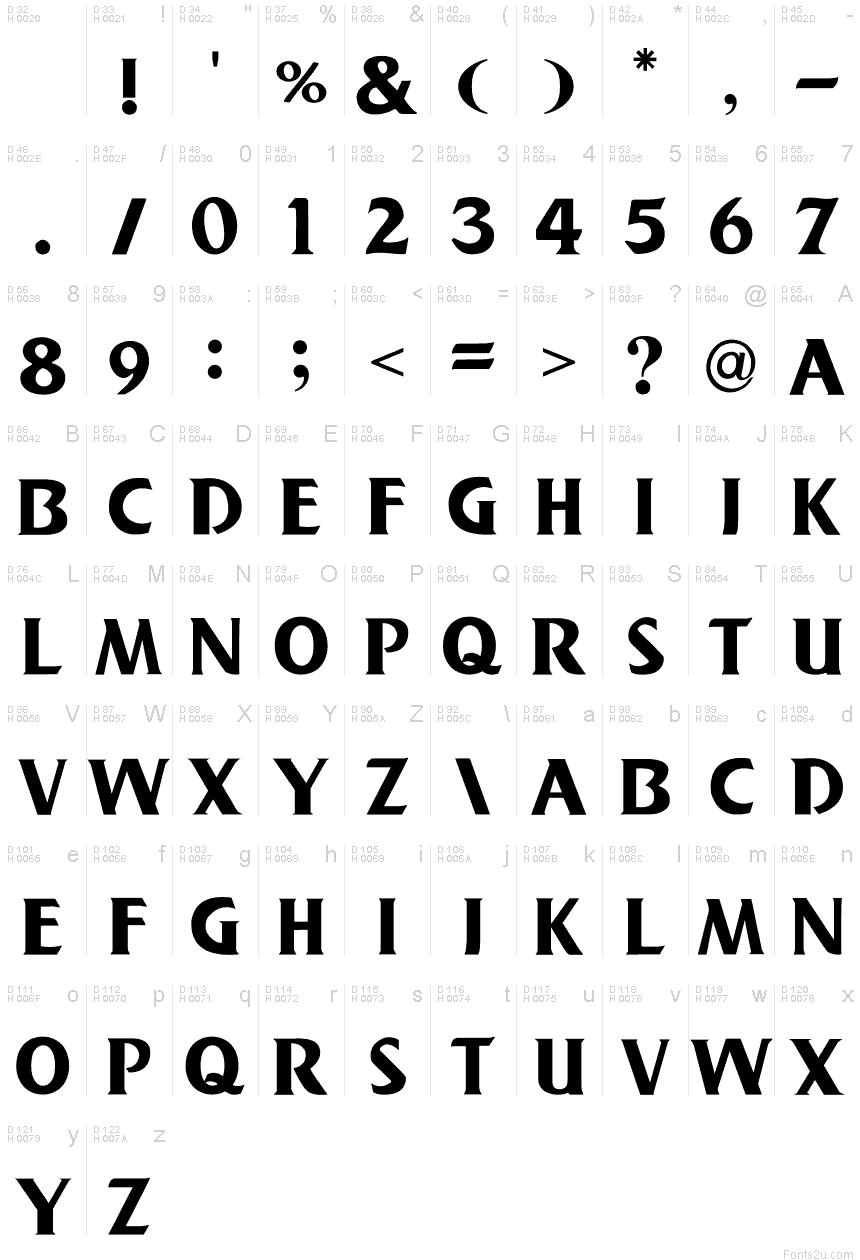
تُعد خط Big Bad Wolf من Sharkshock Productions خط عرض مجانياً بنمط ريترو يتميز بطابع جريء يشبه حكايات القصص. تمنحه الحروف الثقيلة والمتقاربة، والزوائد الحادة التي تشبه الأوتاد، والوقفة العالية والمضغوطة، شعوراً بلوحات الملاهي القديمة أو لافتات الأفلام الكلاسيكية. تحمل أشكال الحروف لمسة درامية ومريبة قليلاً، لكنها مصقولة بما يكفي لتكون واضحة للقراءة بمجرد النظر.
باستخدام Big Bad Wolf، يمكنك إضفاء لمسة قوية على ملصقات أفلام الرعب أو الفانتازيا، وعروض الهالوين الترويجية، وهوية المتنزهات الترفيهية، وأغلفة الكتب، وتصاميم غرف الهروب، وعناوين الألعاب. يتألق هذا الخط المجاني في العناوين الكبيرة حيث تهيمن أشكاله الداكنة والمكثفة على التصميم؛ استخدمه مع خط هندسي بسيط بلا زوائد (sans) في الأحجام الصغيرة للحفاظ على النص المساعد نظيفاً وغير متكلف.